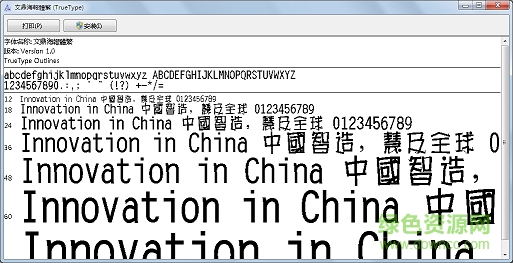
pop1eg bold t gb字體是一款風(fēng)格獨(dú)特的文鼎海報(bào)繁體,字形歪歪扭扭,筆畫(huà)較隨意,一般都是用在海報(bào)設(shè)計(jì)中,顯得非常特別,需要繁體字體的朋友快來(lái)下載吧!
海報(bào)字體,是從用刷子隨意書(shū)寫(xiě)的海報(bào)字形象演化而來(lái)。所以也叫隨意體。橫不平,豎不直,結(jié)構(gòu)也不規(guī)范(例十八)。
其藝術(shù)風(fēng)格:詼諧、隨意、俗野、怪異。